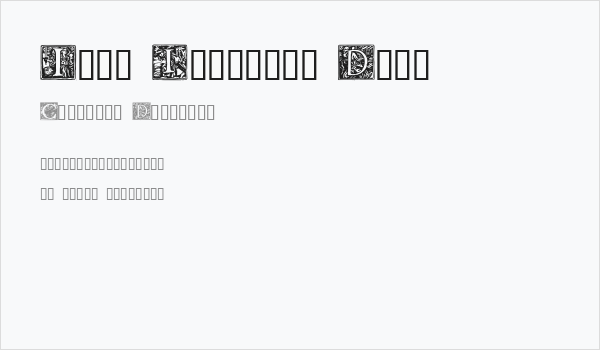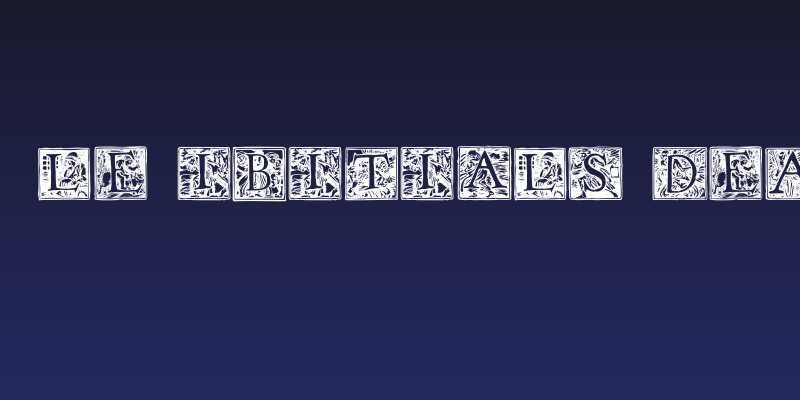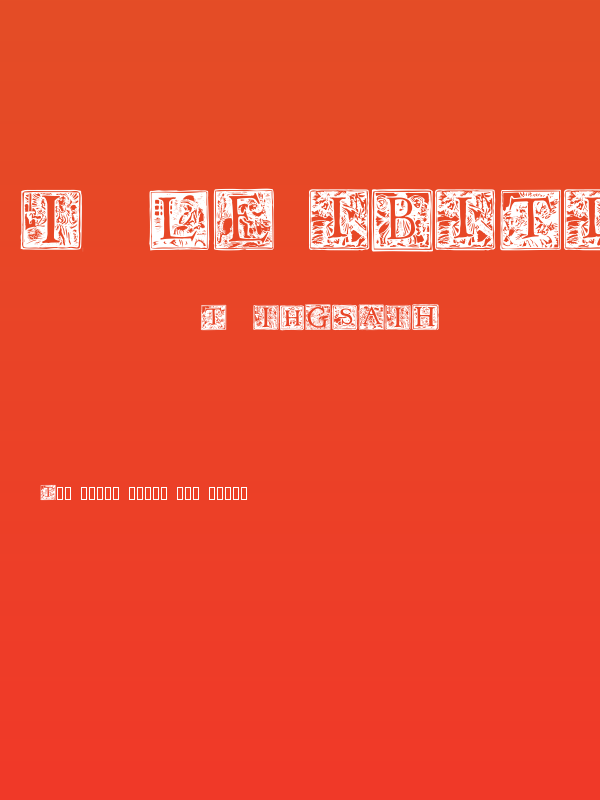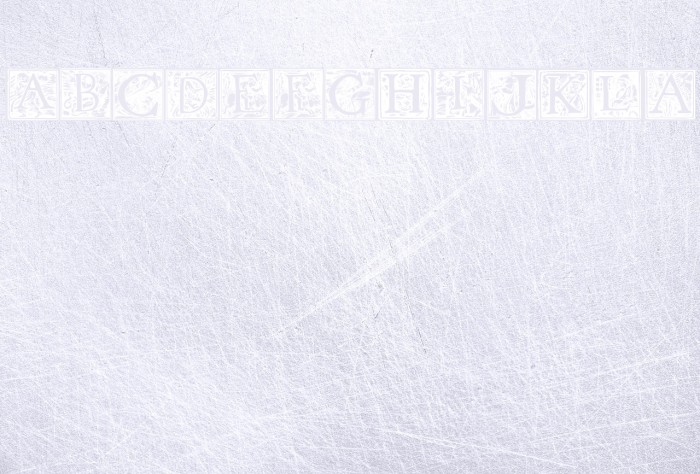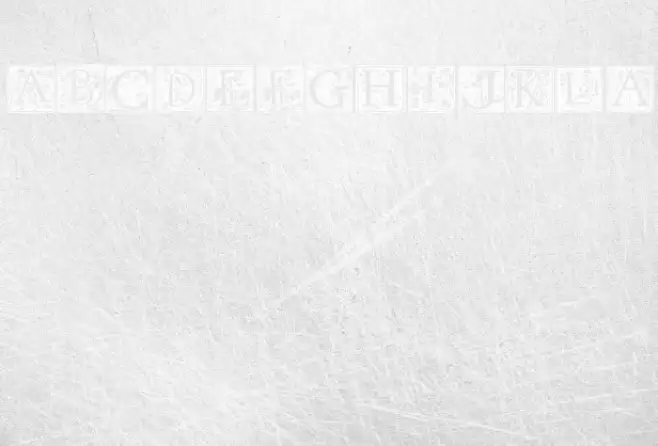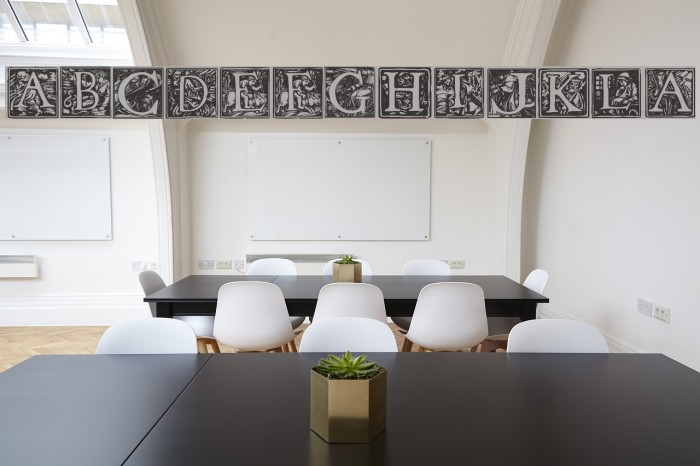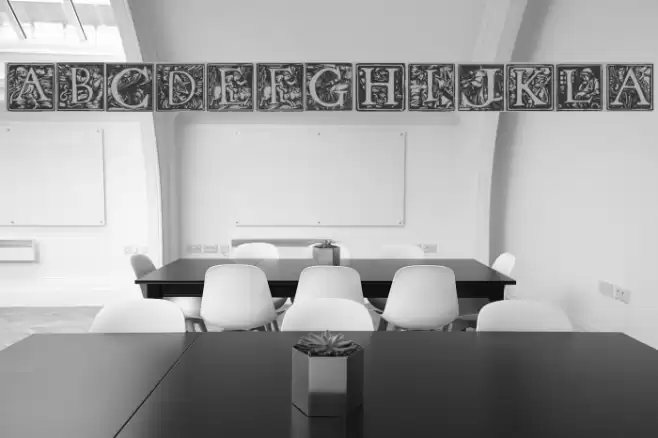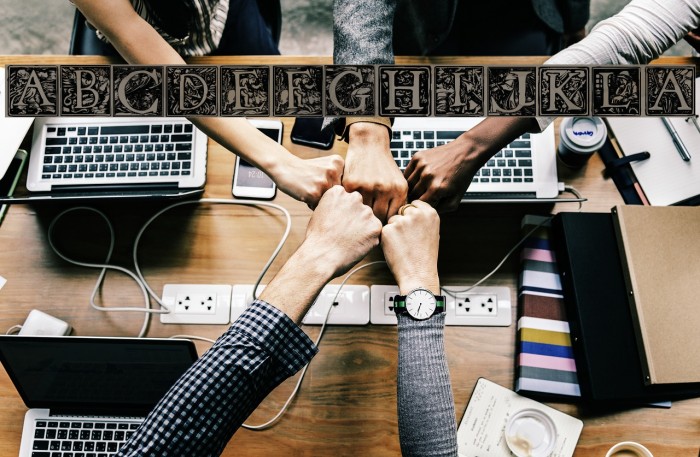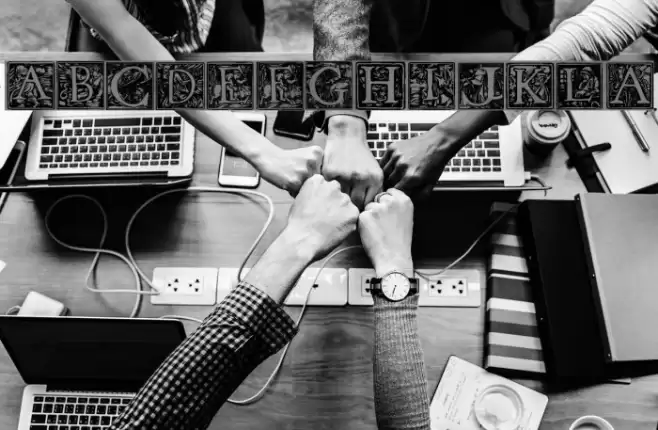
Pyle Initials Demo Font
| カテゴリ | Retro |
| 用途 | Logos, Headlines, Decorative elements |
| おすすめプロジェクト | Perfect for wedding invitations, book covers, certificates, and any project requiring a historical or artistic touch. |